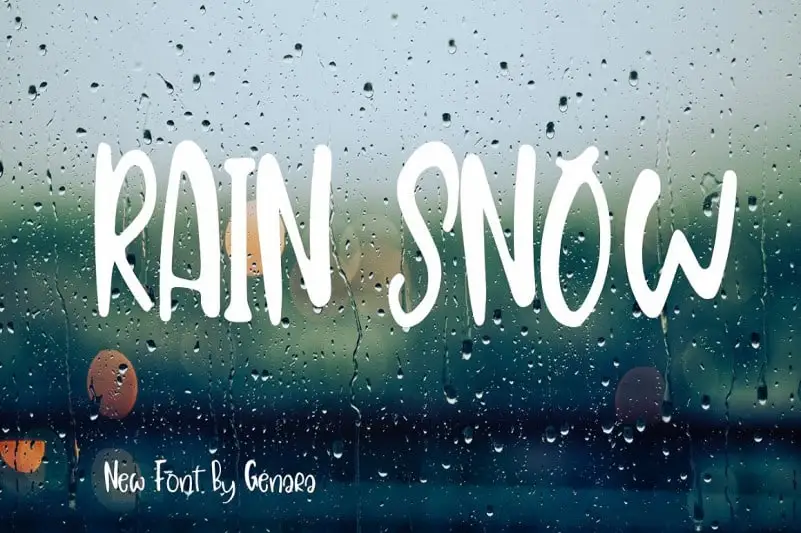
Rain Snow Brush Font – Download Grátis
A fonte ‘Rain Snow Brush Font’ é uma seleção elegante de serifos com um estilo limpo e amigável. Suas linhas naturais e únicas a fazem perfeitamente adequada para diversas aplicações gráficas. Ela pode ser usada em designs variados, desde identidades visuais até materiais publicitários. Seja você designer ou criativo, explore os inúmeros recursos desta fonte, que oferece uma infinidade de possibilidades. Com a ‘Rain Snow Brush Font’, cada projeto ganha um toque único e personalizado.
Designer: Genarastudio